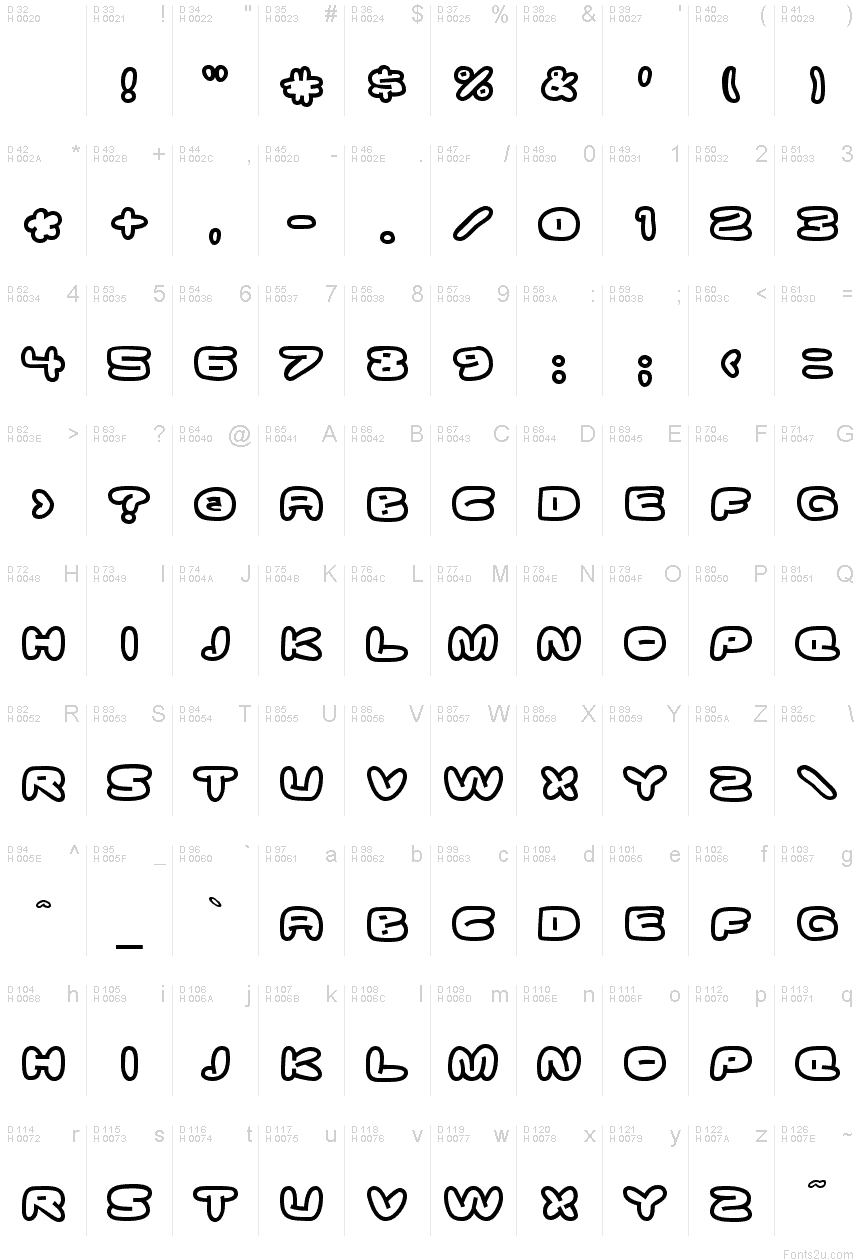
Ghostmeat من تصميم Ray Larabie هو خط مفرغ مجاني بأسلوب القصص المصورة، يبدو وكأنه خُطّ بقلم تحديد عريض على ظهر دفتر ملاحظات مسكون. تتميز الخطوط السوداء السميكة بتموجات خفيفة تجعلها تبدو حية، بينما توحي الأشكال الناعمة والمنتفخة بالود بدلاً من الرعب. إنه خط مرح، يضفي لمسة من الغموض، ويحمل في طياته طاقة رسوم الكرتون الصباحية.
باستخدام Ghostmeat، يمكنك إنجاز تصميمات رائعة لمنشورات حفلات الهالوين، وعناوين أفلام الرعب المخصصة للأطفال، وتغليف المنتجات، وشعارات الألعاب، وصور YouTube المصغرة، أو صفحات القصص المصورة التي تتطلب لمسة من الرعب المضحك. يتألق هذا الخط المجاني في الأحجام الكبيرة حيث يمكن لمحيطه الفقاعي أن يبرز؛ وللنصوص الفرعية، يفضل تنسيقه مع خط بلا زوائد (sans-serif) هندسي ونظيف، لتبقى الحروف الشبحية هي محور الاهتمام.